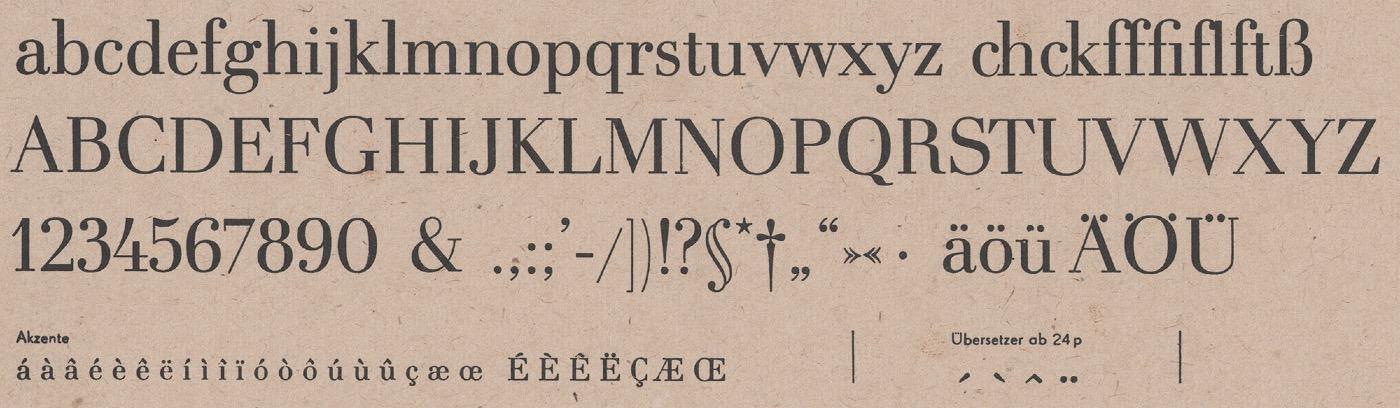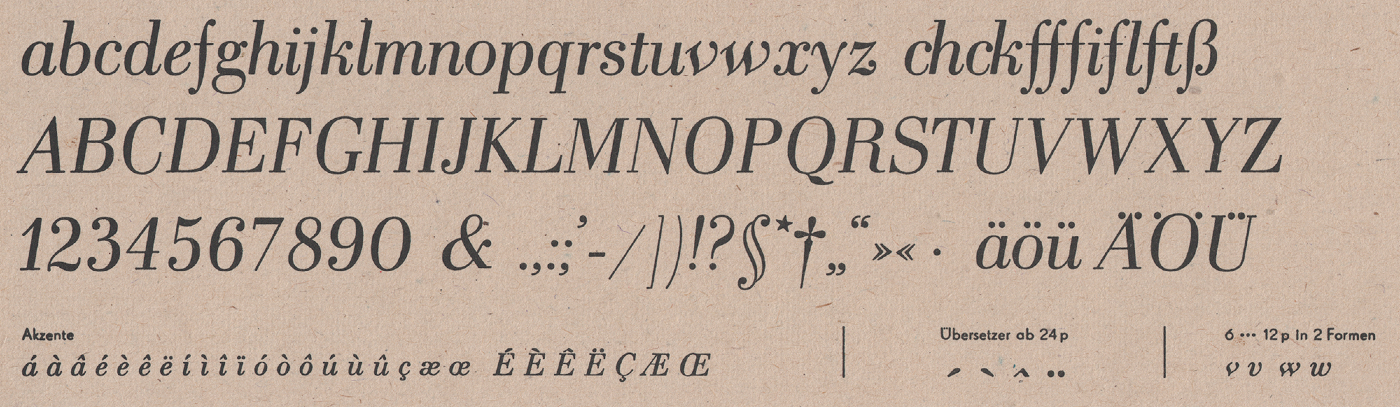
Die Typoart Didot ist ein Neuschnitt der Didot-Schriften nach Zeichnungen von Herbert Thannhaeuser. Die Schrift erschien 1958 als Bleisatzfamilie in drei Schnitten: mager, kursiv und halbfett.